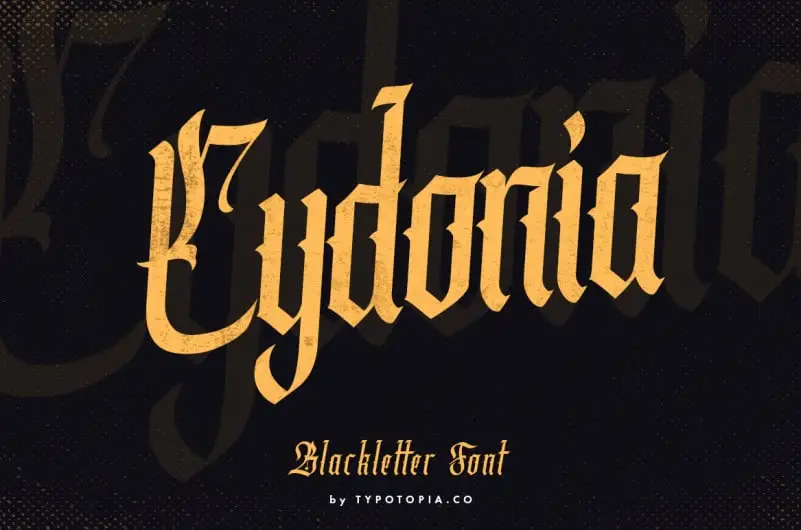
Cydonia Blackletter Font – Download Grátis
Introduzimos a Cydonia Blackletter Font, uma escolha única para designer que busca uma tipografia distintiva. A Cydonia não é apenas qualquer outra letra gótica; ela traz uma riqueza única e originalidade ao seu design. Este font inclui letras maiúsculas, minúsculas e pontuação, além de caracteres internacionais. Esta escolha para o Cydonia é perfeita para um amplo leque de aplicações, desde a headline até logotipos, roupas, convites, marcação, embalagens ou anúncios. A Cydonia se destaca por sua versatilidade e flexibilidade. Perfeito para vários fins, ela atende perfeitamente às necessidades de design que exigem uma estética única e distintiva. Não apenas é aperfeiçoada para uso pessoal em projetos de pequeno porte, como também oferece liberdade para usar comercialmente. Se você está procurando por um fonte Blackletter incrível e único, a Cydonia seria uma escolha perfeita. Para obter as licenças comerciais necessárias para usar o Cydonia em ambientes de negócios, consulte nossas lojas online ou sites dedicados ao fornecimento desta ferramenta gráfica avançada.